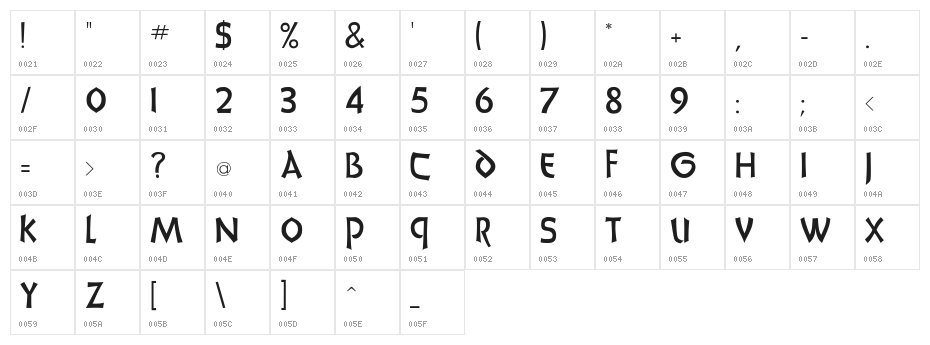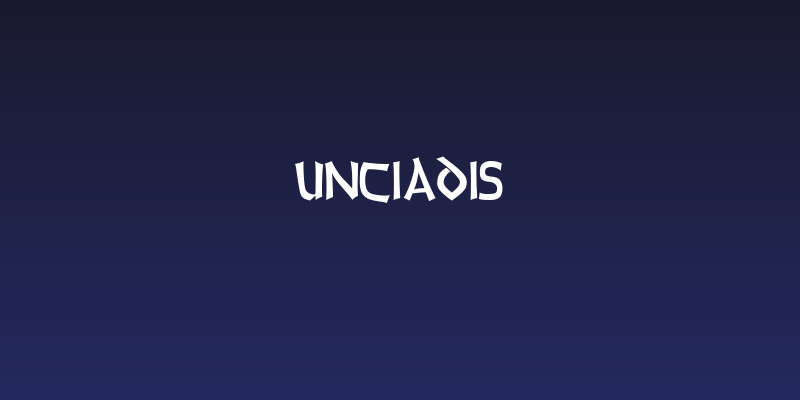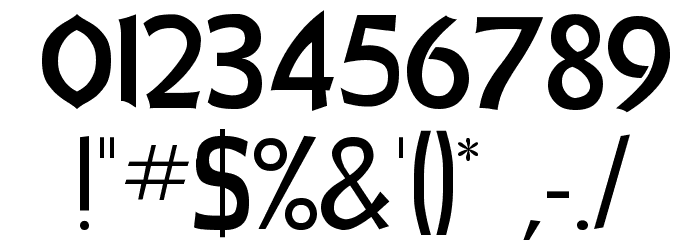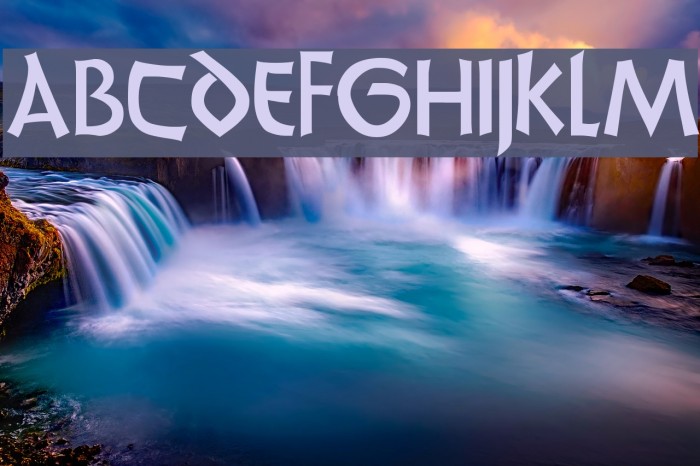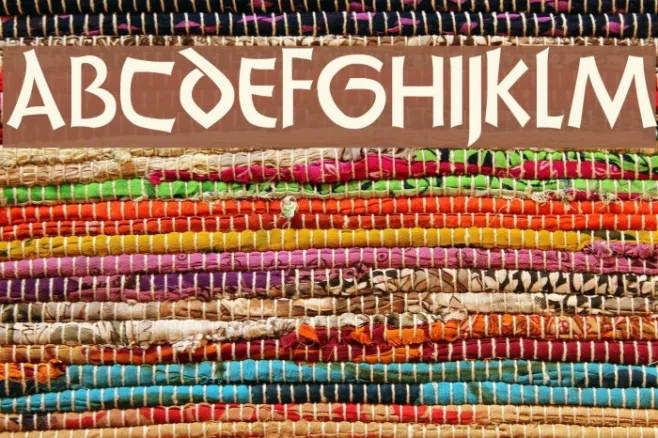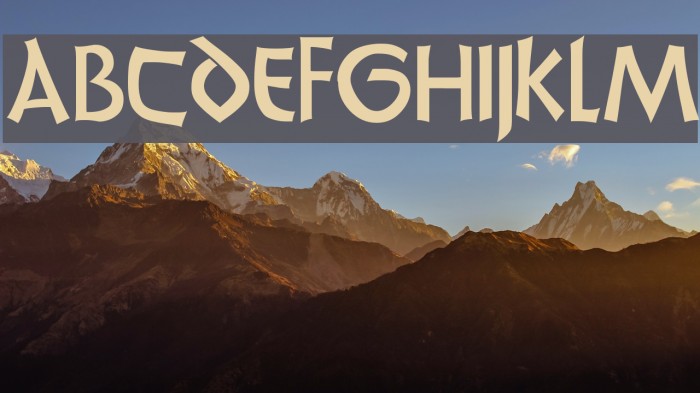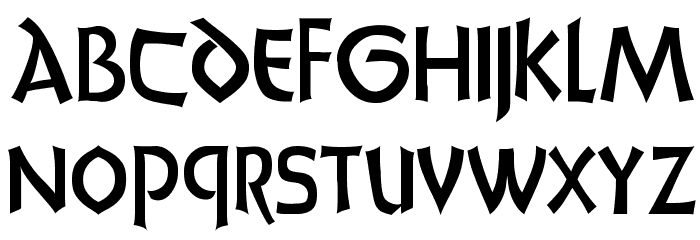
UnciaDis Font
| Vorgeschlagene Projekte | Ideal for fantasy-themed designs, video game titles, book covers, and branding that requires a strong, distinctive look. |